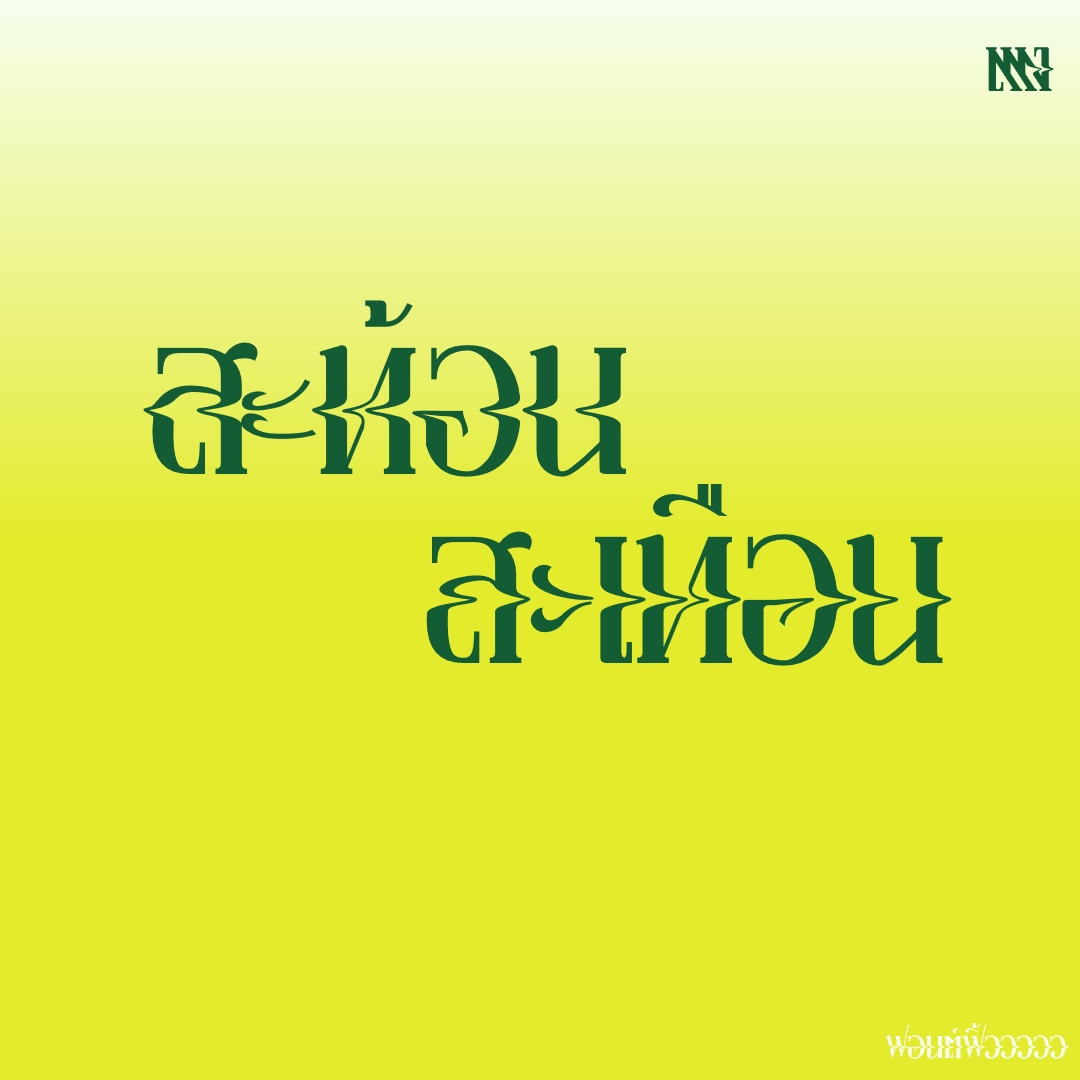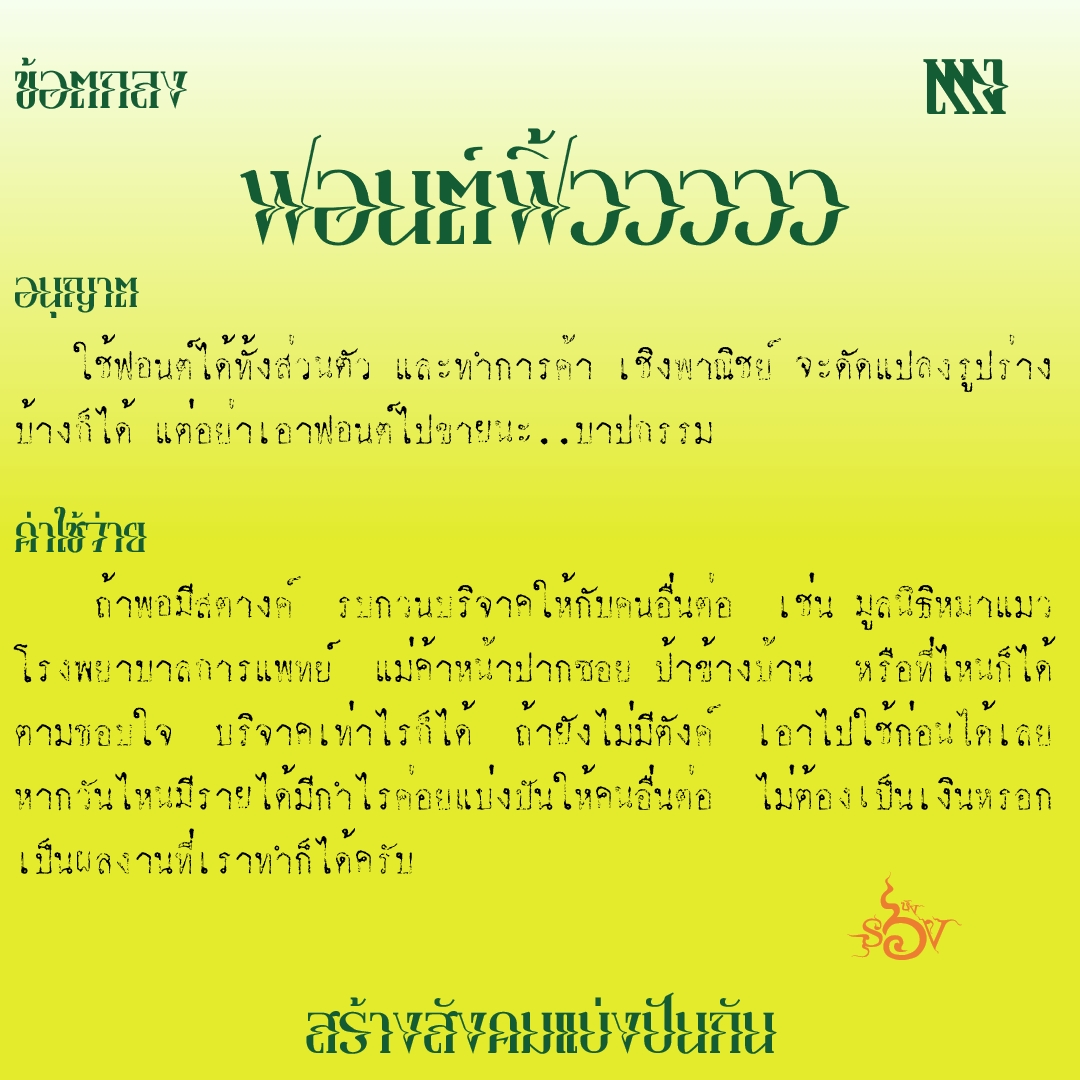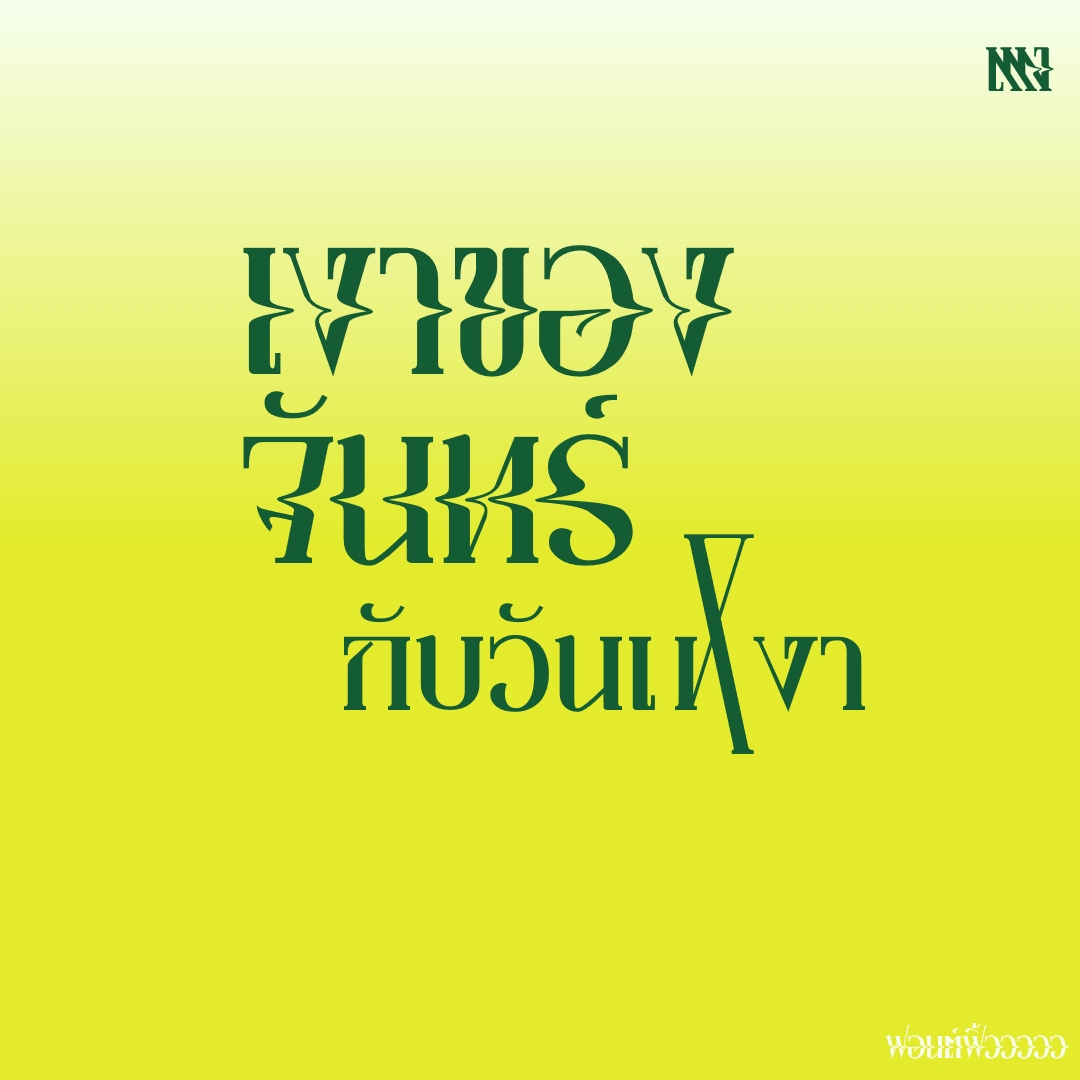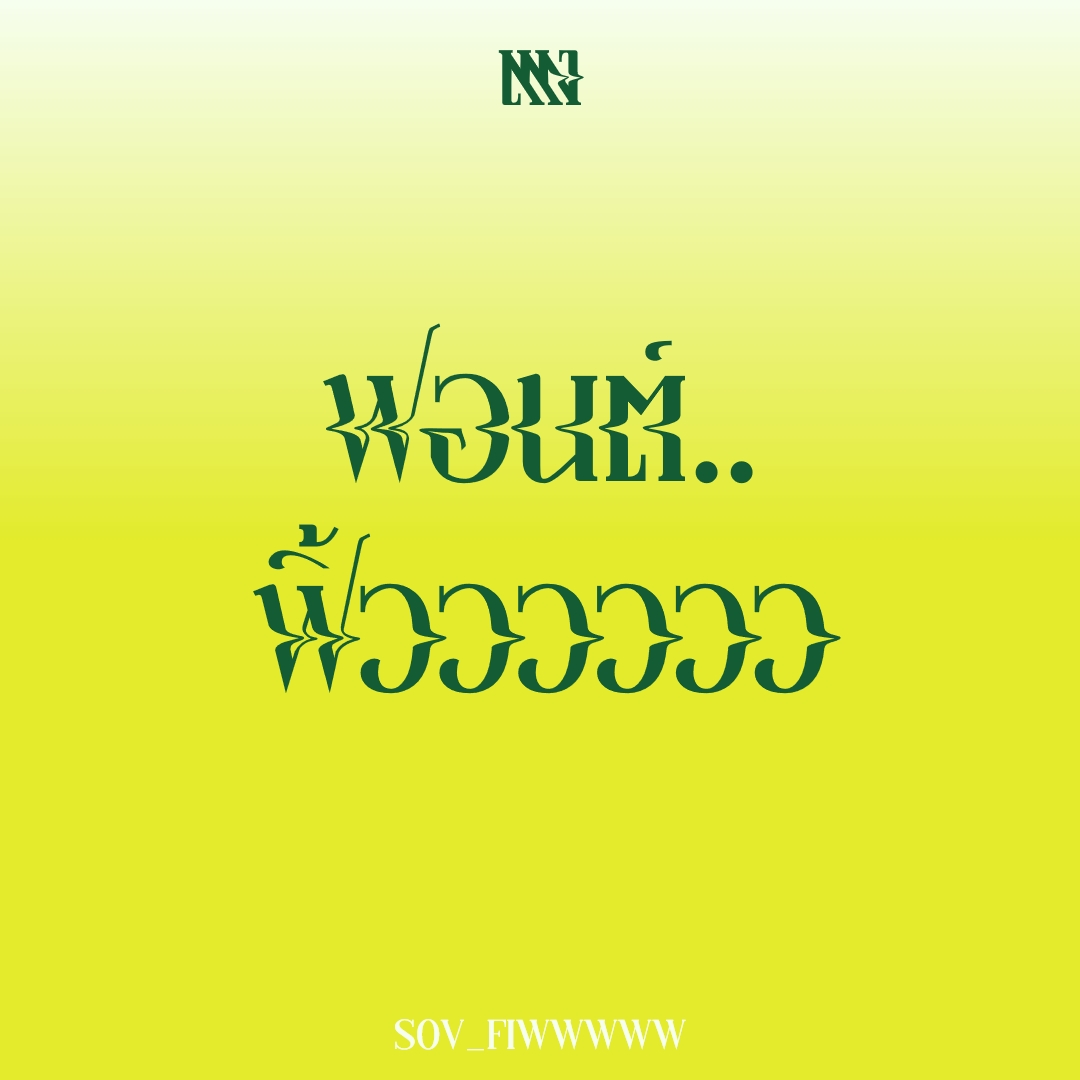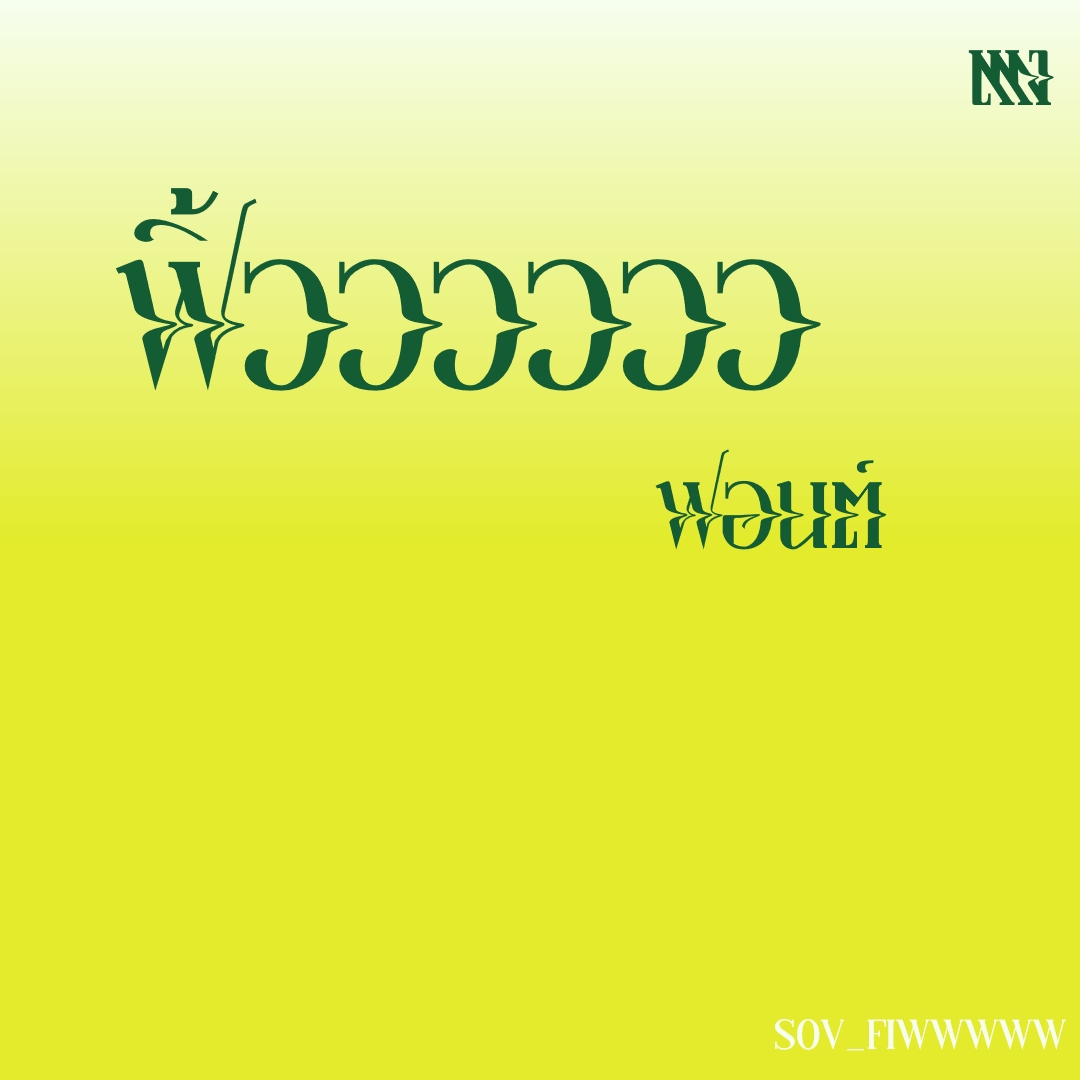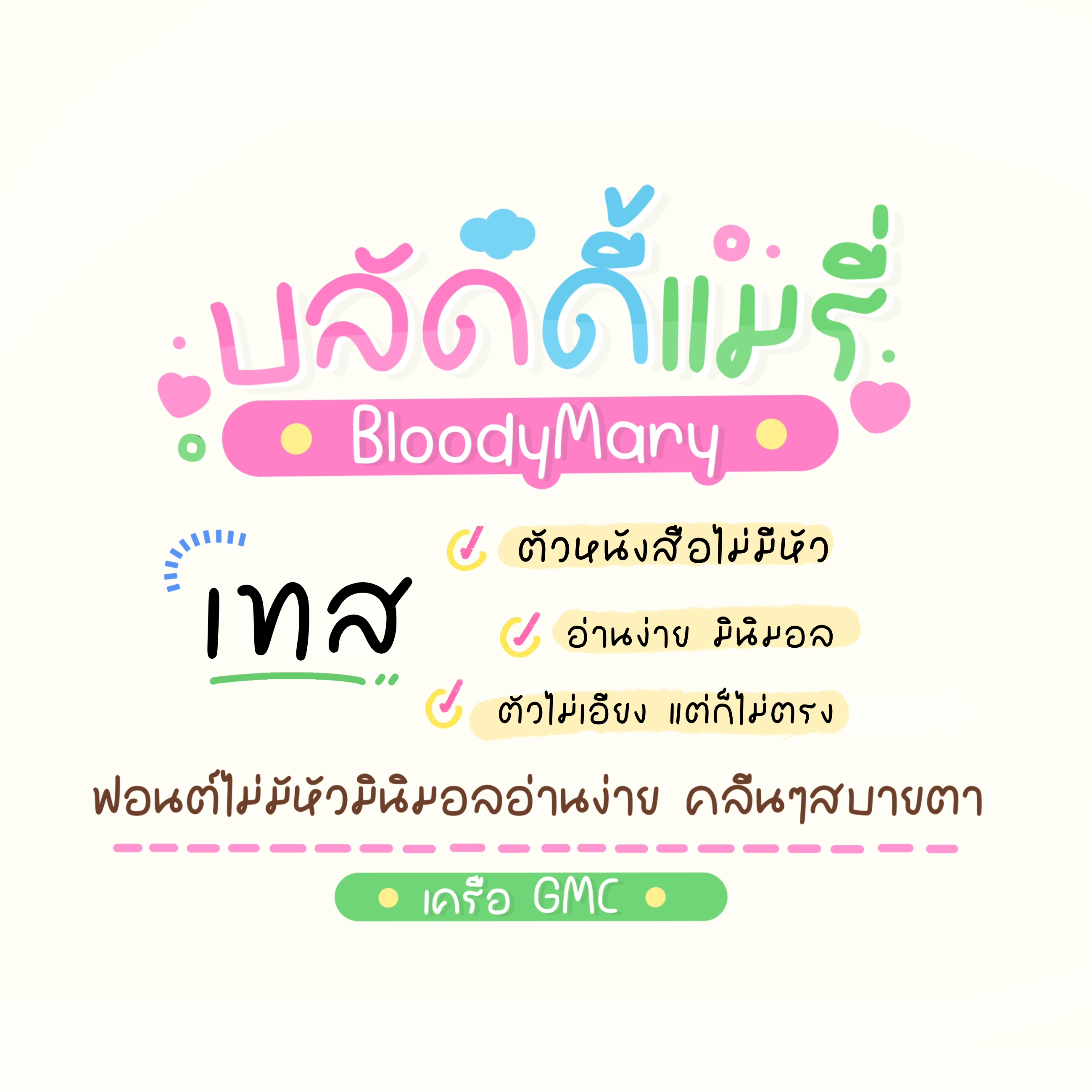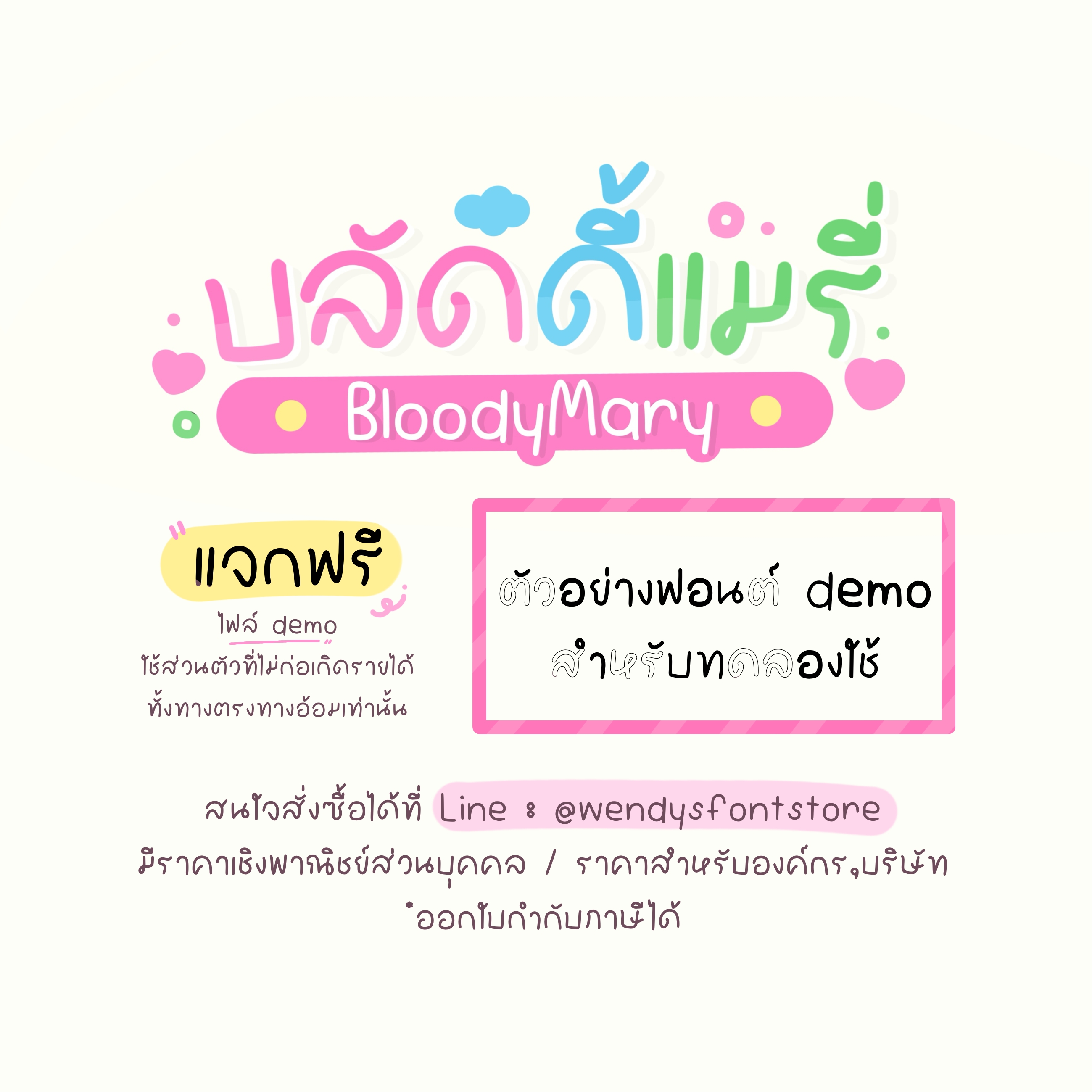
ชื่อฟอนต์ : ฟิ้ววววว
ฟอนต์ตัวนี้ให้นึกภาพว่า เอาแปรงทาสีร่างตัวอักษรเสร็จ แล้วเอากิ่งไม้เล็กๆ ลากขวาง..ฟิ้ววววว (ตัวปรกติฟิ้วววววไปขวา ตัวหนาฟิ้วววววไปซ้าย)
ฟอนต์มะเขือเทศ [RDTomato]
ชื่อฟอนต์ : บลัดดี้แมรี่  (GMCctBloodyMary)
ฟอนต์ลายมือ คุกกี้ (LMF Cookie)